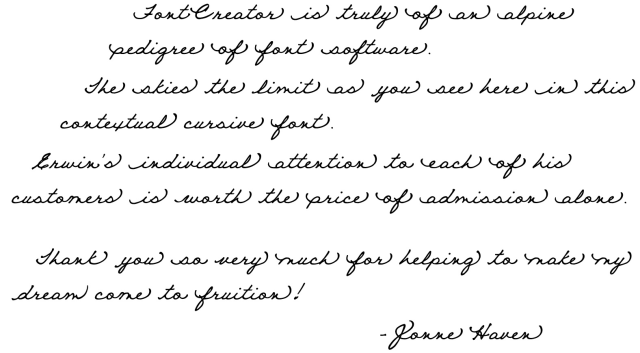
Learn how to create handwritten fonts with contextual alternates using FontCreator's OpenType features. 本教程介紹如何使用 FontCreator 的 OpenType 特性創建帶有上下文替代的手寫字體。
calt 功能進行這些替換。
為什麼上下文替代很重要
文本形狀引擎的挑戰
a.start、a.between1、a.between2、a.end 分別用於起始、兩個中間和結束版本。介紹 calt 功能
calt(上下文替代)功能是實現上下文替換的關鍵。我們將設置查找表來識別單詞邊界並替換適當的字形。功能代碼分解:
languagesystem latn dflt; # Latin default
@letter = [a-z];
@letter.start = [a.start];
@letter.between1 = [a.between1];
@letter.between2 = [a.between2];
@letter.end = [a.end];
lookup SingleSubstitutionEnd { # GSUB lookup type SingleSubstitution
sub @letter by @letter.end;
} SingleSubstitutionEnd;
lookup SingleSubstitutionBetween { # GSUB lookup type SingleSubstitution
sub @letter by @letter.between1;
} SingleSubstitutionBetween;
lookup SingleSubstitutionStart { # GSUB lookup type SingleSubstitution
sub @letter by @letter.start;
} SingleSubstitutionStart;
lookup SingleSubstitution1 { # GSUB lookup type SingleSubstitution
sub @letter.between1 by @letter.between2;
} SingleSubstitution1;
feature calt { # Contextual Alternates
lookup ChainingContextStart { # GSUB lookup type ChainingContext
ignore sub @letter.start @letter';
ignore sub @letter.between1 @letter';
ignore sub @letter @letter';
sub @letter' lookup SingleSubstitutionStart @letter;
} ChainingContextStart;
lookup ChainingContextBetween { # GSUB lookup type ChainingContext
sub @letter.start @letter' lookup SingleSubstitutionBetween @letter;
sub @letter.between1 @letter' lookup SingleSubstitutionBetween @letter;
} ChainingContextBetween;
lookup ChainingContextEnd { # GSUB lookup type ChainingContext
ignore sub @letter' @letter;
sub @letter.start @letter' lookup SingleSubstitutionEnd;
sub @letter.between1 @letter' lookup SingleSubstitutionEnd;
} ChainingContextEnd;
lookup ChainingContextRotate { # GSUB lookup type ChainingContext
sub @letter.between1 @letter.between1' lookup SingleSubstitution1;
} ChainingContextRotate;
} calt;